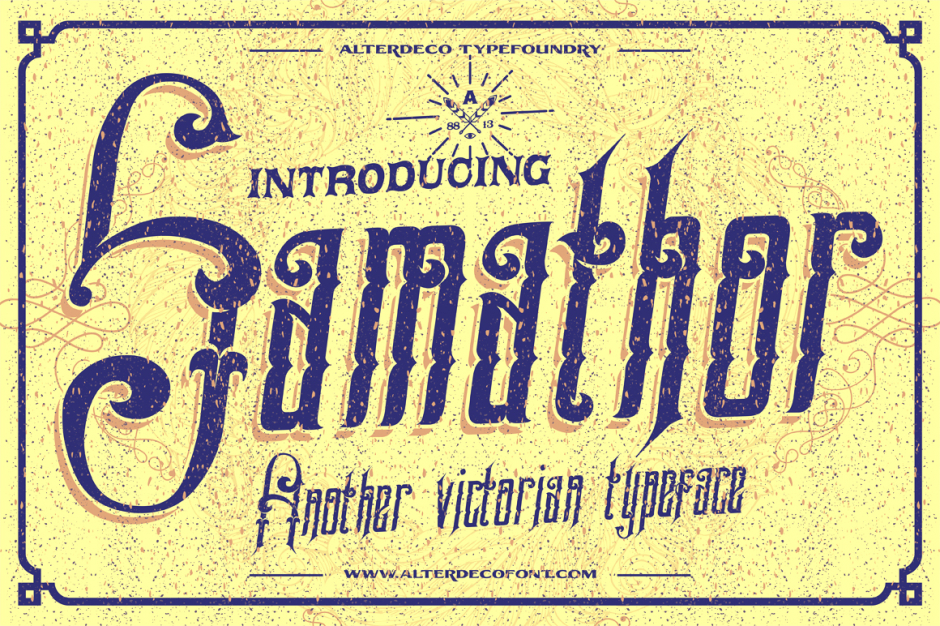
A Samathor Typeface é uma tipografia inspirada no estilo vintage Victoriano, criada com amor e meticulosamente por mãos humanas. Inspirada na natureza, ela traz um charme único que se destaca em logotipos, letras chamativas, frases de autor, cartões personalizados, flyers e até mesmo postais. Com uma aparência acintosa e elegante, a Samathor é perfeita para qualquer aplicação gráfica, seja ela uma carta de boas-vindas ou um poster promocional. Seja qual for seu projeto, essa fonte de estilo Display do 178-MC irá tornar o seu trabalho ainda mais brilhante e imprimível.